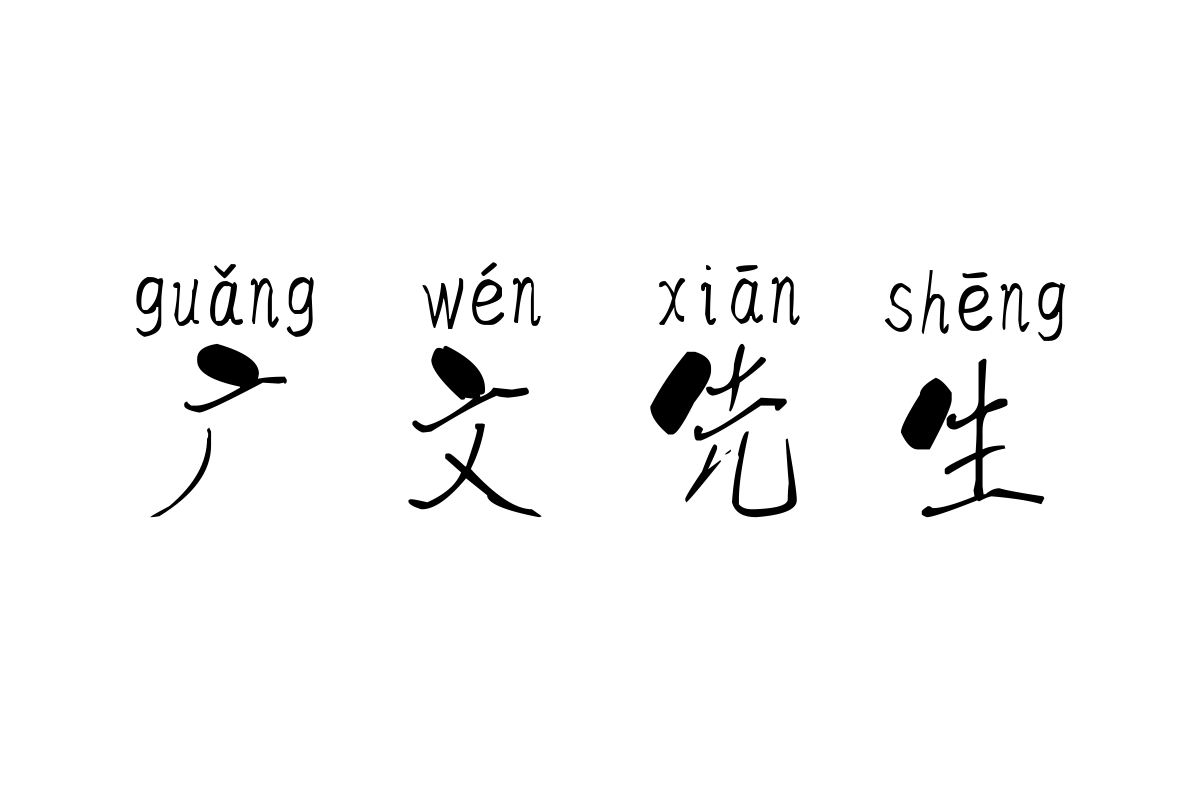
汉标精工阿叶拼音字体是一款专为中文排版设计的字体,具有独特的风格和特点。这款字体的特点是笔画流畅、字形优美,适合用于各种中文文本的排版设计。
1. 笔画流畅:汉标精工阿叶拼音字体的笔画线条顺滑,给人一种舒适的感觉。这种笔画流畅的特点使得字体看起来更加美观,同时也便于阅读。
2. 字形优美:汉标精工阿叶拼音字体的字形结构紧凑,线条交错有序,给人一种优美的视觉享受。这种字形优美的特点使得字体在视觉上更具吸引力,能够更好地传达出文字所要表达的情感和意境。
3. 适用范围广泛:汉标精工阿叶拼音字体适用于各种中文文本的排版设计,包括书籍、杂志、报纸、广告、网页等。无论是正式的文件还是创意的设计,这款字体都能够提供良好的支持。
总之,汉标精工阿叶拼音字体是一款具有独特风格和特点的中文字体,适合用于各种中文文本的排版设计。它的笔画流畅、字形优美、适用范围广泛等特点使其成为了许多设计师和排版师的首选字体之一。